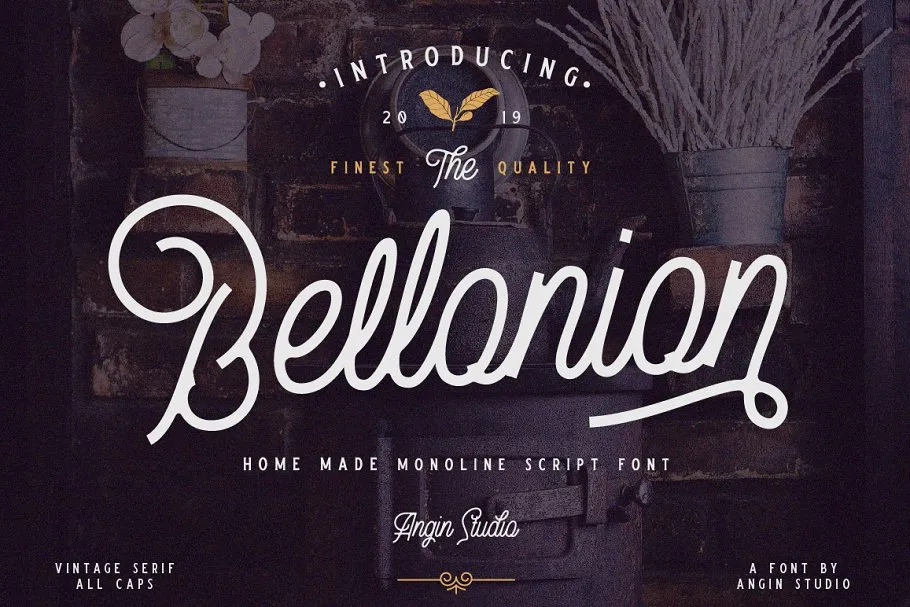
A Bellonion Font Duo é uma elegante combinação de serifada e script que oferece um toque autêntico aos designs digitais. Desenhada pelo Studio Angin, essa fonte monoline apresenta traços delicados criados a partir da letra feita à mão. A intenção era criar algo cuidadosamente meticuloso para manter sua personalidade única e despertar emoções diferentes em cada uso. Com alternativas de caracteres, Bellonion permite que você junte e misture as letras de maneira inovadora e expressiva, adicionando um toque especial ao seu trabalho. Esta fonte, perfeita tanto para serifada quanto para script, é uma excelente escolha para designers buscando dar vida à sua arte digital com um toque único e autêntico.